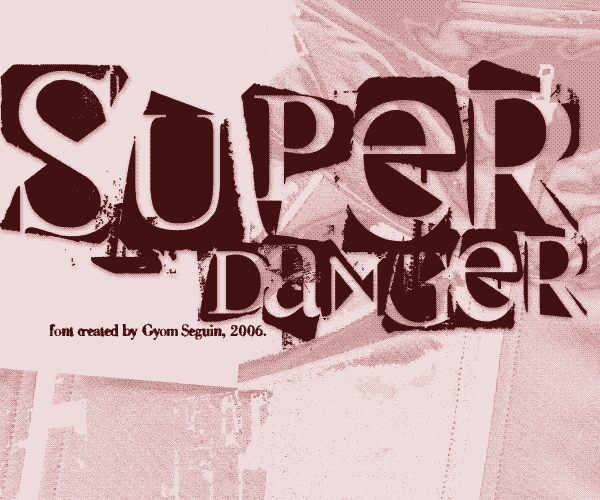
Super Danger od GYOMSEGS to darmowy font display w stylu grunge collage o surowym charakterze wycinanki. Litery wyglądają, jakby zostały wyrwane z różnych źródeł – ciężkie szeryfy mieszają się tu z nierównymi blokami, postrzępionymi krawędziami i gwałtownymi cięciami, co nadaje całości nerwowy, niemal improwizowany wygląd.
Dzięki temu świetnie sprawdzi się na punkowych ulotkach, okładkach zinów, płytach, plakatach i tytułach, gdzie typografia może pełnić rolę tekstury, a nie uporządkowanego brandingu. Jako darmowy font do krótkich tekstów, idealnie nadaje się do nagłówków lub inicjałów – jego poszarpane kontury i nieregularne wypełnienia robią całą robotę.